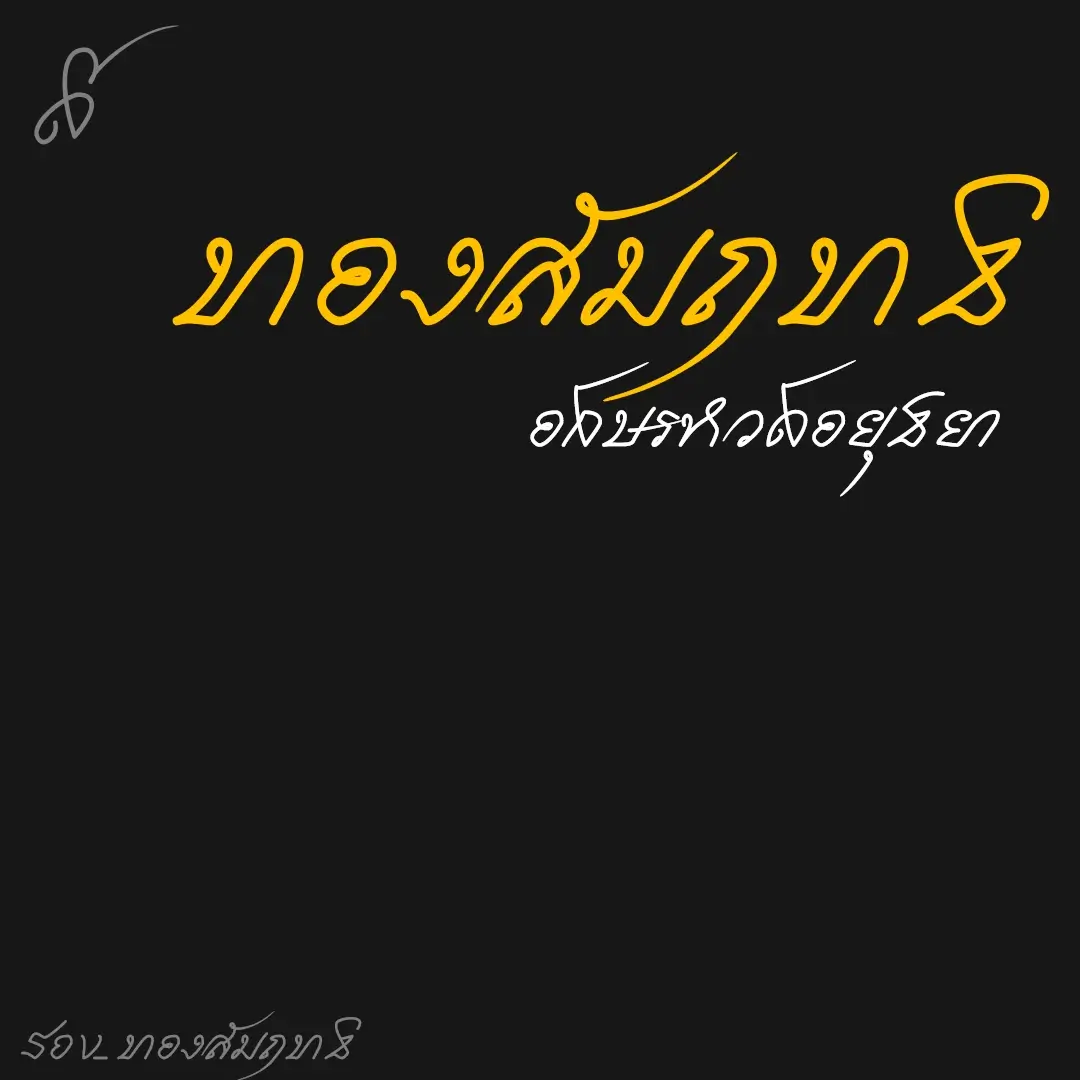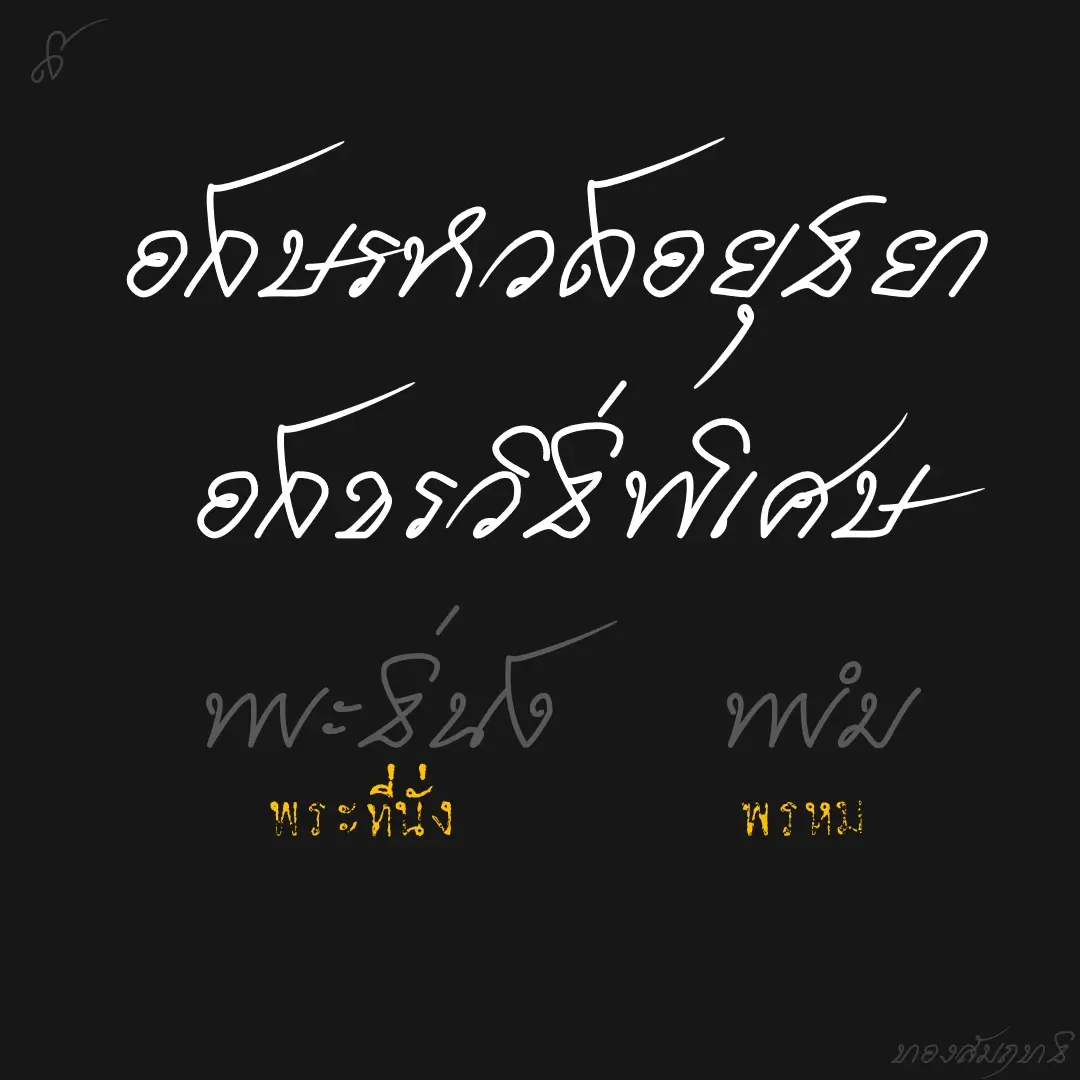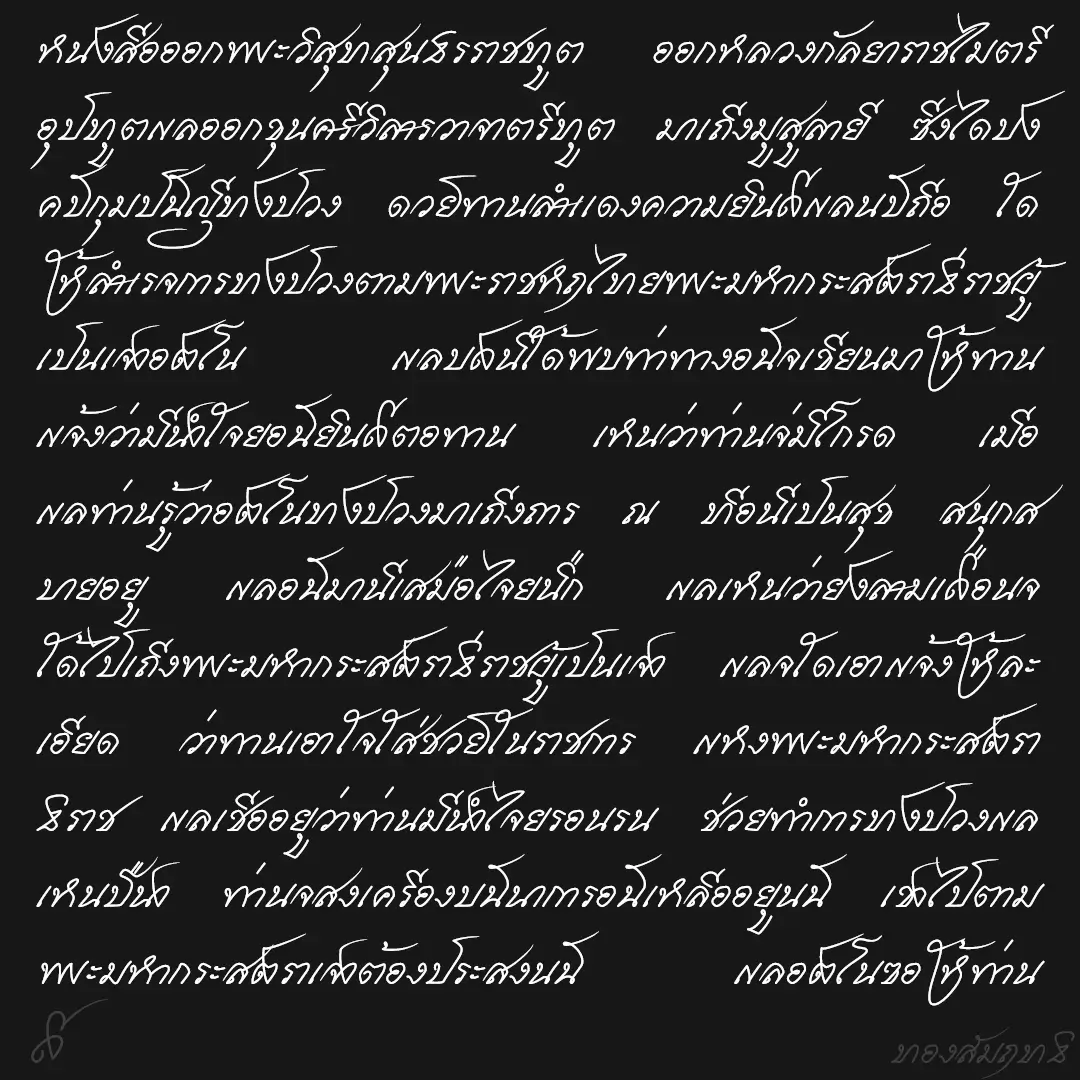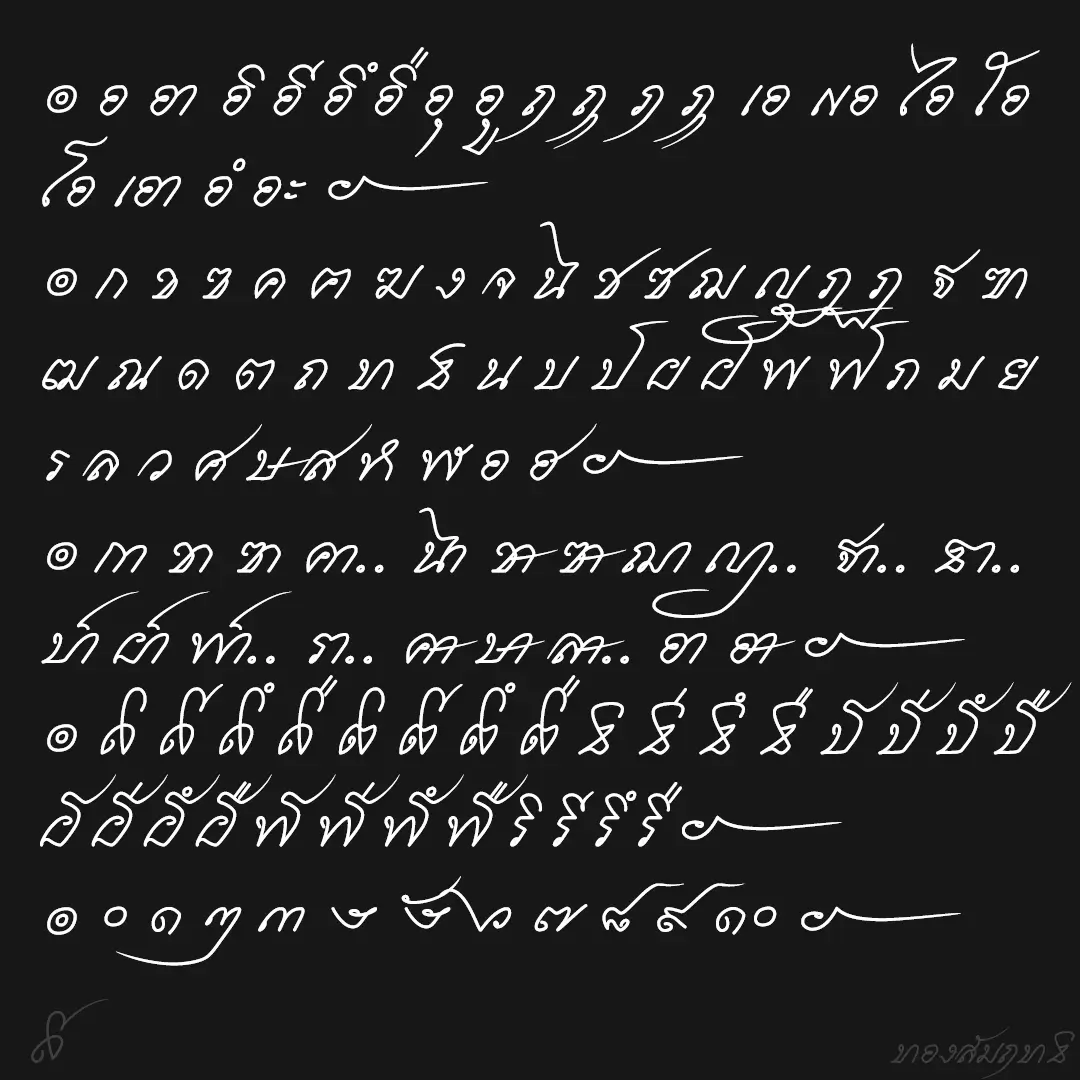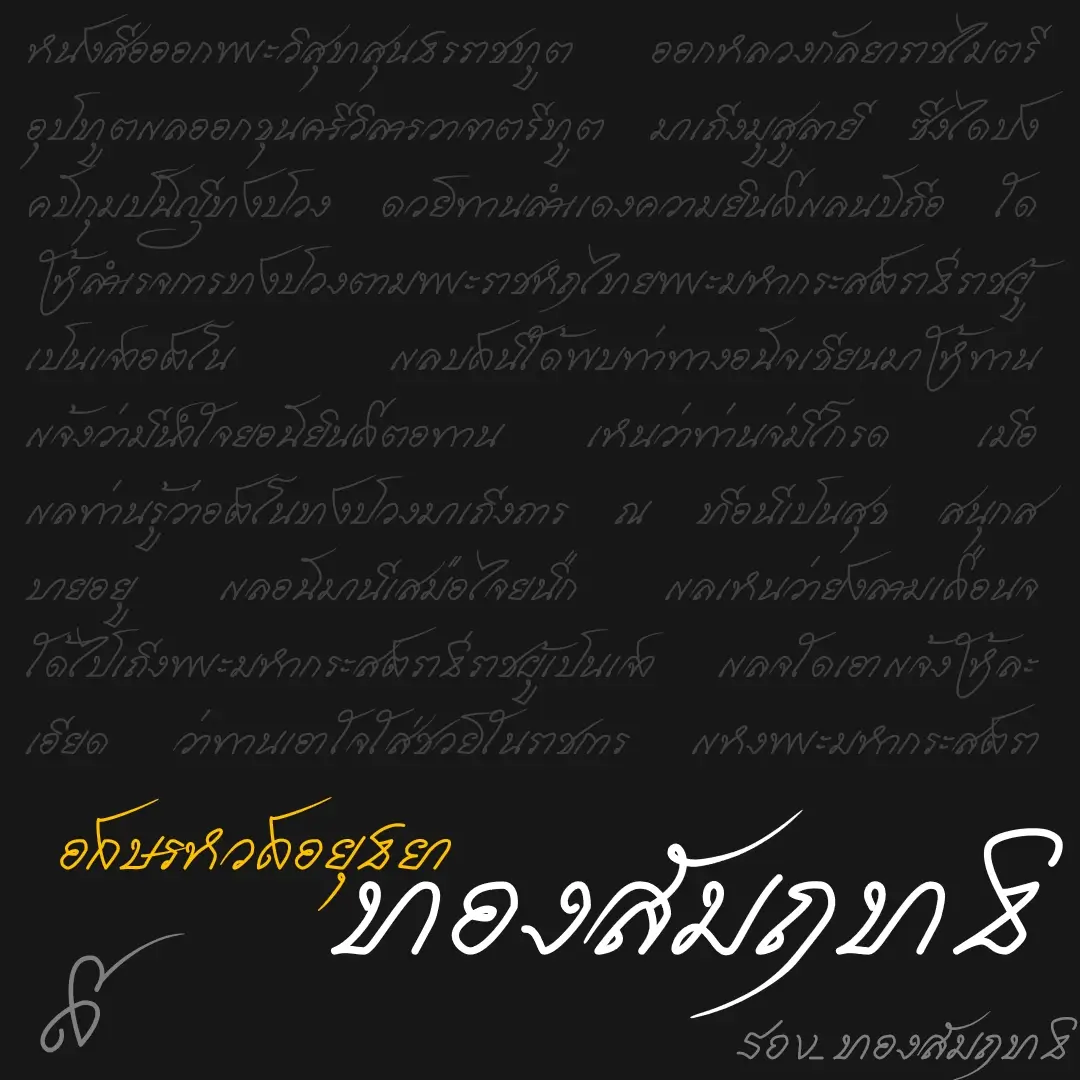
ฟอนต์ทองสัมฤทธิ์ – ได้แนวคิดจากอักษรหวัด สมัยอยุธยา โดดเด่นที่การรวบอักษร เชื่อมอักษร พยัญชนะ-พยัญชนะ พยัญชนะ-สระ พยัญชนะ-วรรณยุกต์ สระ-วรรณยุกต์ นอกจากนี้ยังมีการใช้พยัญชนะเดียวประสมสองรูป เช่น ในี (ในนี้) และอื่นๆ
ด้วยอะไรไม่รู้ หลังจากพิมพ์ข้อความไปครบหน้า แล้วลองกดปุ่มเอียง… ได้แต่ร้อง..อุ๊ย!!
เบื้องหลังการออกแบบ : ฟอนต์ ทองสัมฤทธิ์
ทองสัมฤทธิ์ (SOV_tongsamrid)